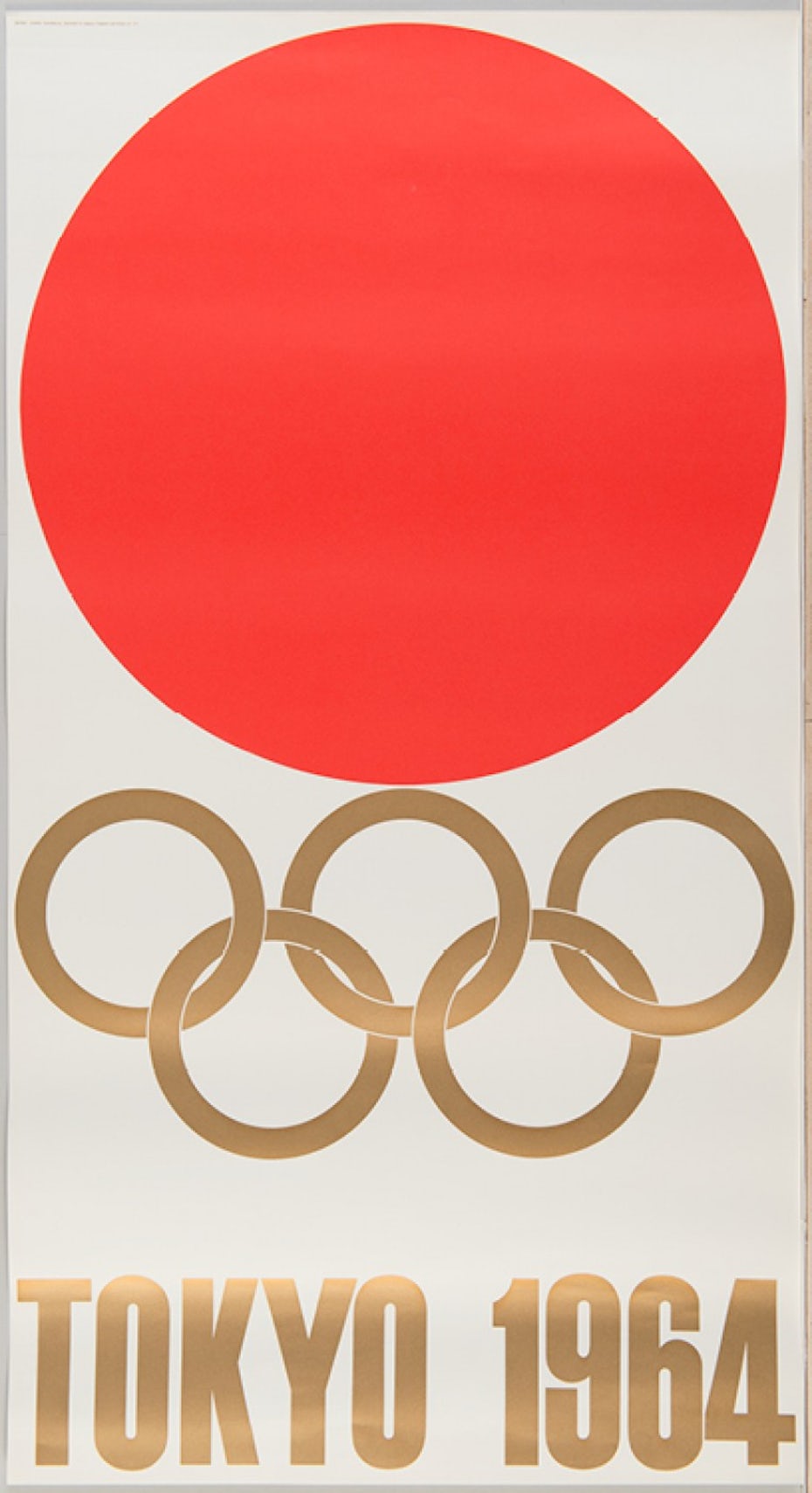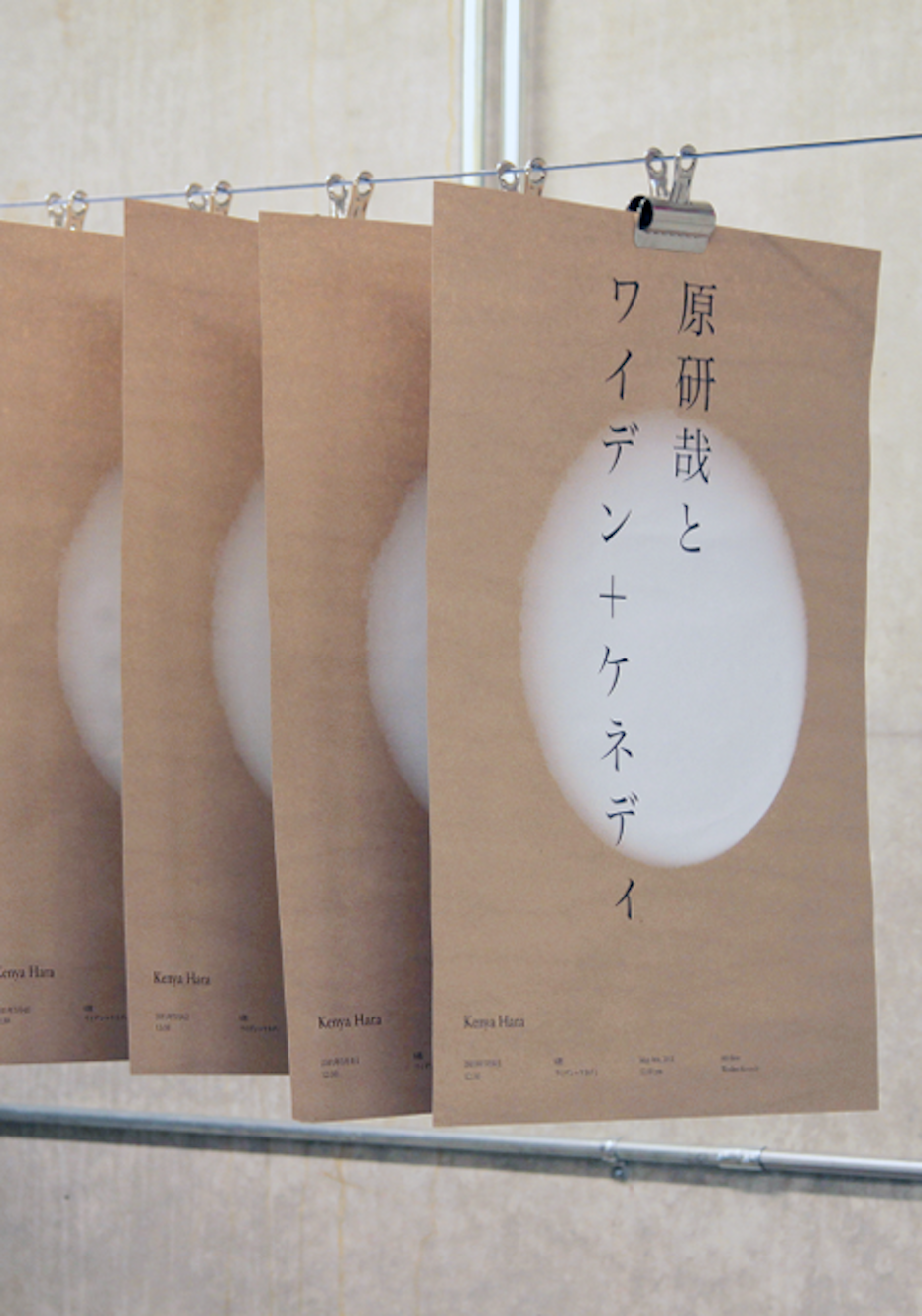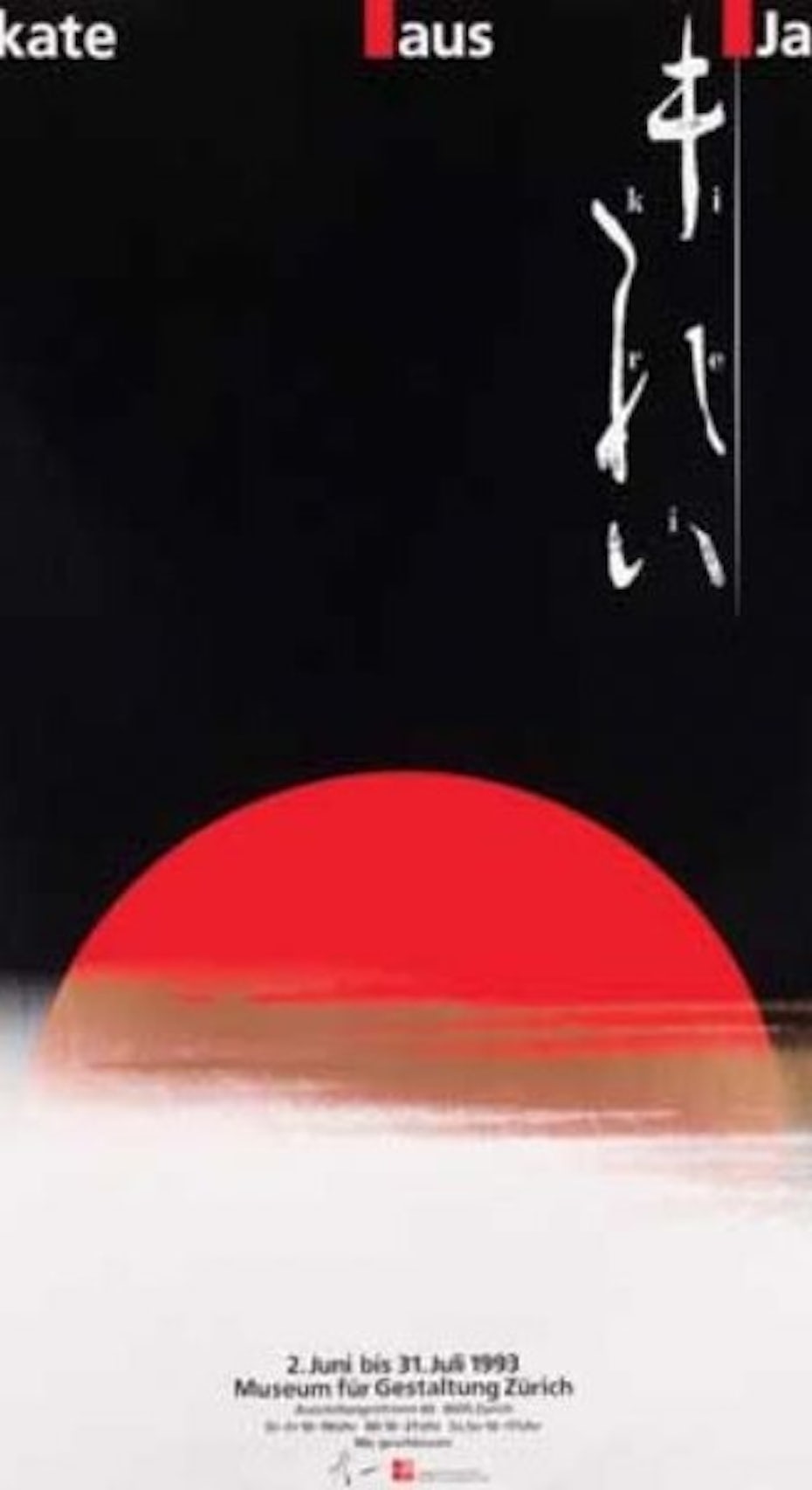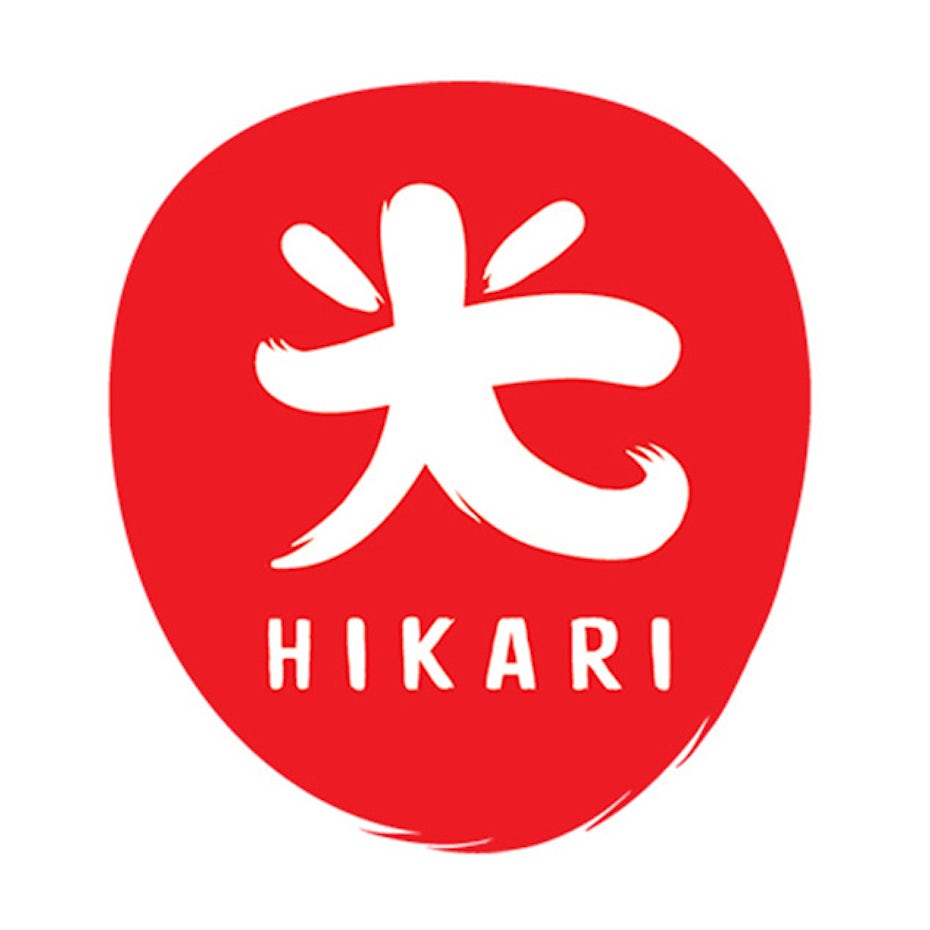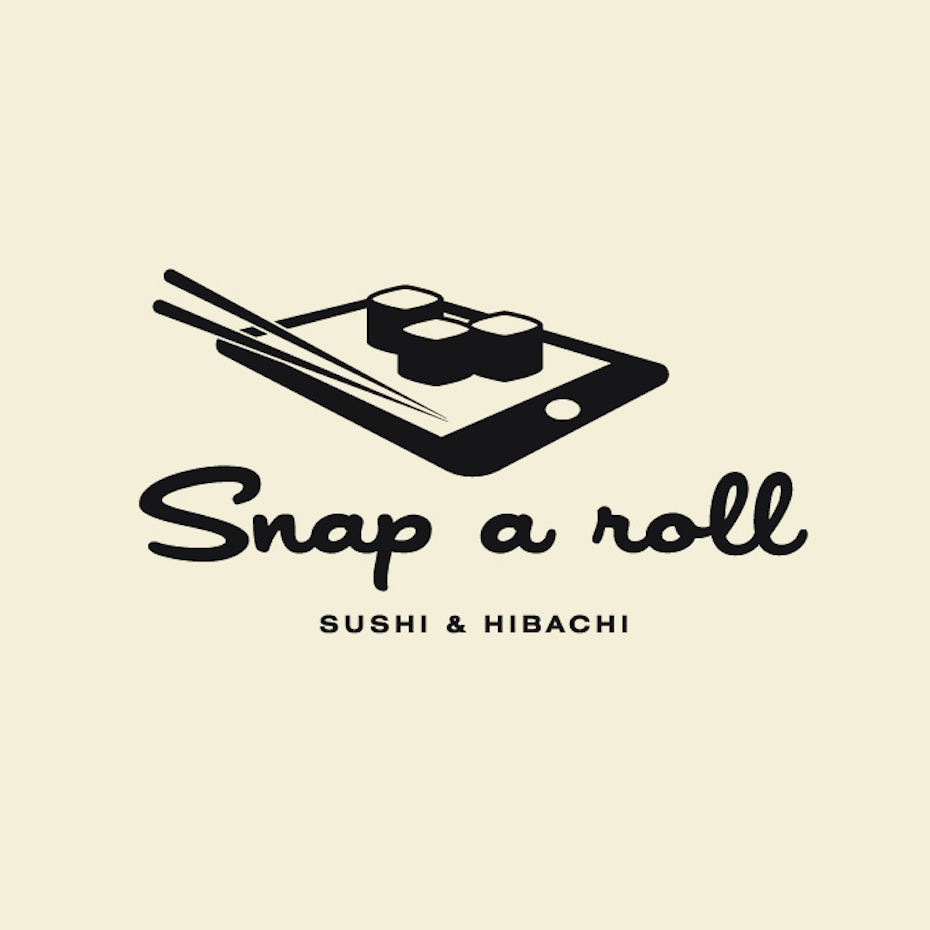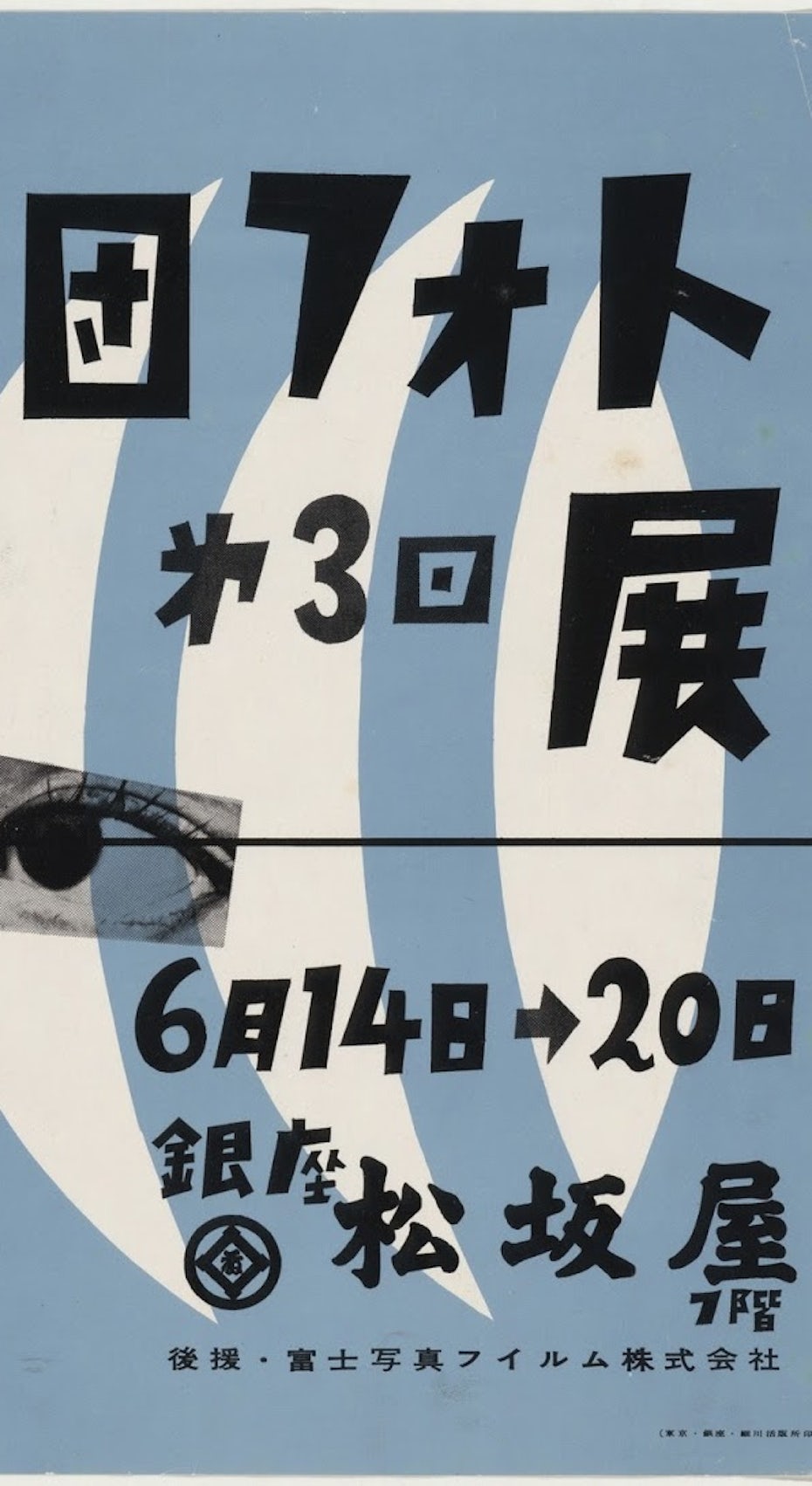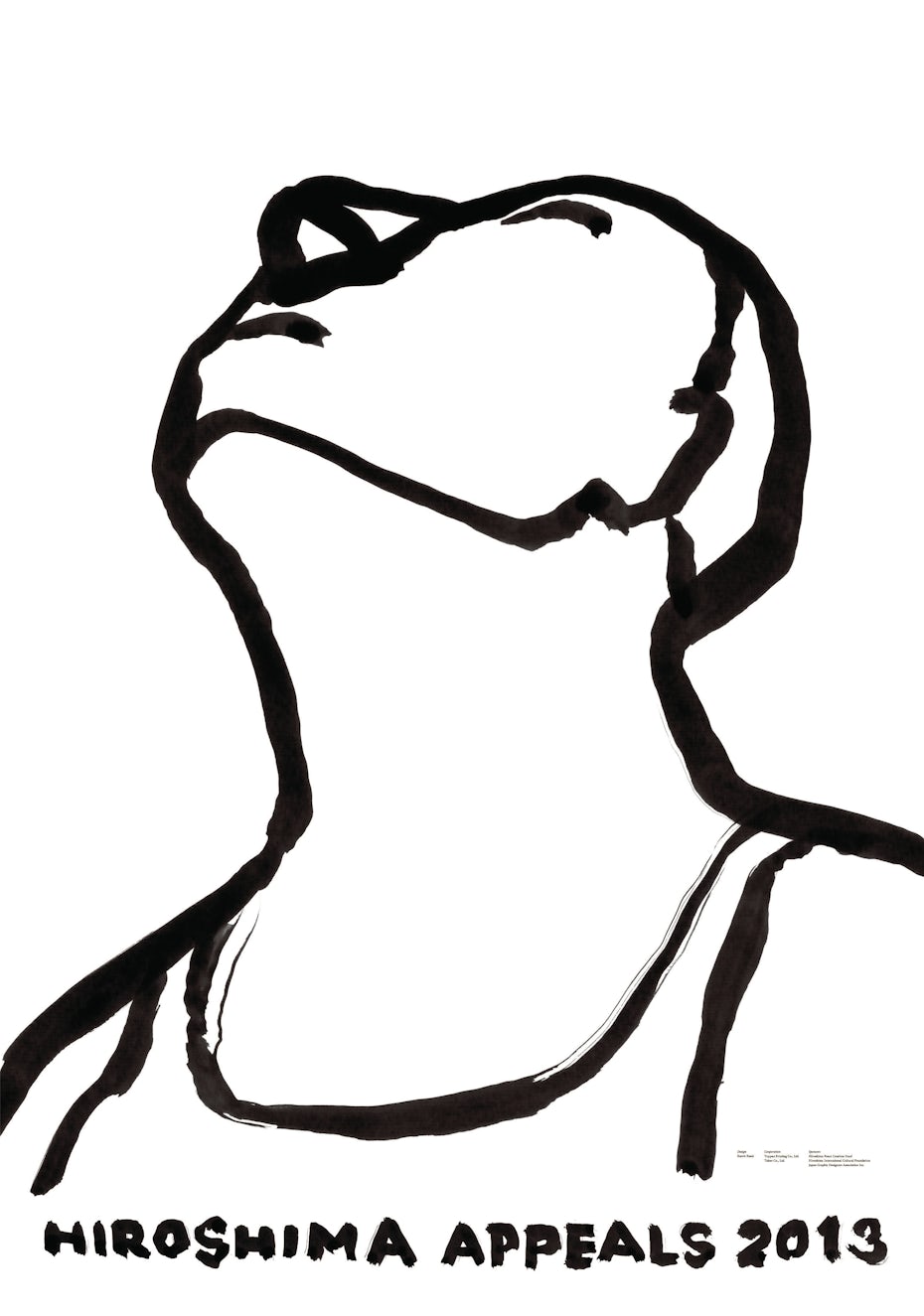
如何将日本元素融入到作品中去?
日本设计自豪地参考了数千年的日本传统艺术,同时也具有现代性和现代性。风格清晰有力的声音从简单的设计、几何图形和彩色斑点到响亮的吉祥物、可爱的图案和卡通。
从极简主义到流行,我们可以看到日本设计在整个西方及其他地区的影响力。
让我们一起来看看如何将日本设计灵感融入到自己的作品中!
日本设计简史
日本的设计总体上受到周围世界的严重影响。日本是一个拥有各种手工艺传统的国家。陶瓷,木版画,书法,折纸,歌舞伎剧场,以及最近的漫画和动漫都只是那里开发的一些艺术品。这些艺术形式影响了数百年的西方艺术和设计 - 例如,日本木刻版画影响了许多着名的西方艺术家,如古斯塔夫克里姆特和文森特梵高。
17世纪—19世纪
在江户时代(1603-1868),日本在经济和文化上蓬勃发展。设计和创意也蓬勃发展。日本广告商是他们销售产品和服务方式的先驱,创造了大规模的海报,印有排版的图形,以及日间相扑手和流行的歌舞伎剧场演员的明星插图。在Instagram出现之前,他们使用影响者营销已有数百年了!
浮世绘是日本木版画和绘画艺术的重要流派,也是在此期间发展起来的。它以女性美,歌舞伎,相扑选手,民间故事和风景等共同主题为特色。由于它很容易印刷,浮世绘变得分布广泛并迅速普及。
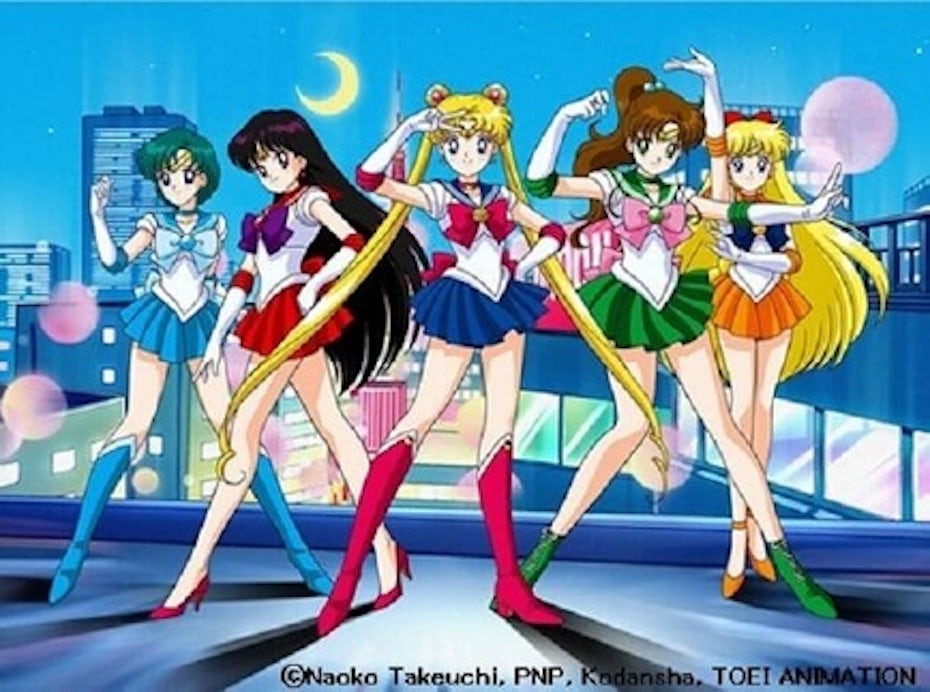
浮世绘后来演变成现代插图、漫画,动漫,甚至电子游戏。这些新风格具有更流行的审美和色彩,通过漫画,漫画小说和玩具对西方产生了巨大的影响。
19世纪后期
在明治时代(1868-1912),日本开放了与世界其他地区的边界,欢迎贸易文化和设计的交流。在西方艺术和设计的启发下,这导致未来50年日本设计的创造力爆炸式增长。
20世纪50年代到80年代
第二次世界大战后,日本经济大幅增长,最终成为世界第三大经济体。在战后年代的工业化和制造业的推动下,建构主义和包豪斯的风格激发了当今的设计,使用强烈的几何形状和日本象征。
20世纪90年代到21世纪
在90年代,日本设计以前所未有的方式爆炸。随着后现代主义和Photoshop和Illustrator等计算机软件的普及,人们可以获得一个全新的设计世界,日本人完全接受了它。
这一时期也让日本的设计更加关注社会责任。1991年至1992年,日本经济崩溃,国家进入了经济停滞时期,称为“失落的十年”,持续到2010年。
设计师试图通过摆脱过度行为并且带来平衡,从而在经济复苏期间积极影响人们工作。
今天,日本设计对全球变暖和污染等环境问题更加关注。由于人口众多且生活空间有限,设计师必须考虑人们如何消费他们的产品。因此,日本设计获得了相当自然的基调。
像Marie Kondo一样,摆脱任何不必要的东西。在传统的日本美学中,Wabi-Sabi是一个以接受禅宗和中国道教的不完美为中心的世界观。
基本上,它在不完美中找到快乐并摆脱所有不会激发快乐的东西。
Wabi-Sabi与现代主义有很多共同点,但它更直观,不对称,温暖,流畅。这种技术试图保持设计的本质而不会失去诗意。清洁,但不是无菌的,简单而聪明。
尝试将日本极简主义带入您的品牌,徽标,包装,网站等。
2.自然运动
许多最早的日本木版印刷块说明了自然以及世界如何不断变化和移动。这种连续感演变成现代漫画和明亮的包装。
3.自然
日本文化具有惊人(和令人生畏)的自然特征,如地震,火山和台风,对环境非常敏感。日本人民像其他人一样庆祝自然和季节。这种影响也带来了创意设计解决方案。
建筑设计借鉴了木材和石材等元素。在平面设计中,大自然进入包装材料,自然插图和泥土色调调色板。
4.几何
日本设计非常注重几何元素,因为形状具有更深刻的文化含义。
正方形和矩形代表自然界中不常见的人造形式,通常用于制作和服,漆盒,箱子,屏风和一些陶瓷的轮廓。曲线和圆弧代表直觉和灵感。
5.排版
日语排版比西方字母复杂得多,书法在日本设计中起着巨大的作用 - 绘画字母本身就是一种艺术形式。
现代日语由三种基本文字组成:汉字(汉字表意符号)和平假名和片假名(语音符号)。因此,日语的字体数量有限,而且为任何设计项目定制排版是很常见的。
6.象征意义
日本的民间传说,所有的东西都有自己的精神 - 甚至是像石头或盒子一样无生命的东西。这就是为什么在产品中添加面孔和类似人的品质如此常见的原因。你会看到这广泛用于广告,海报,包装和品牌。
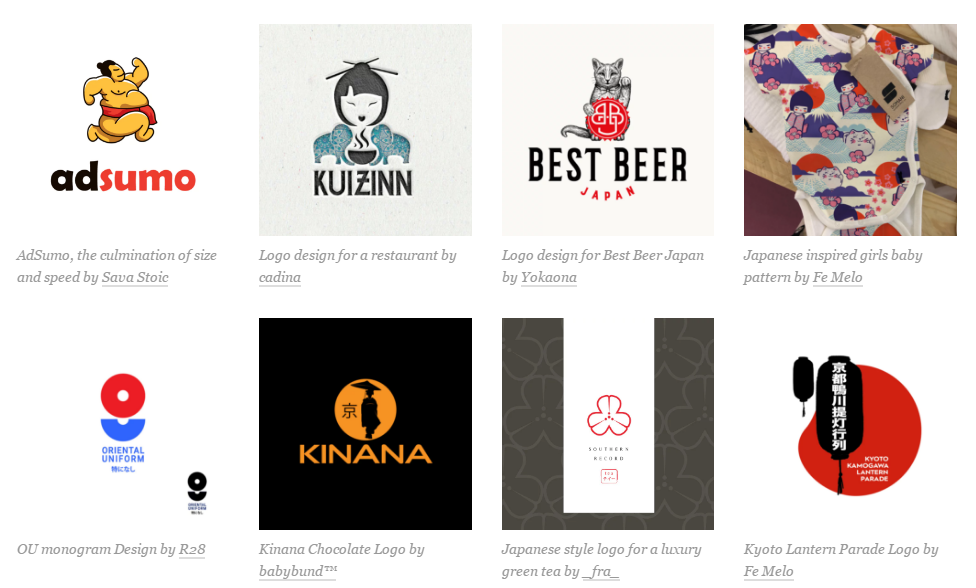
传统融入了日本设计,如果你看到很多富士山,旭日,幸运猫或相扑选手的照片,不要感到惊讶。符号的运用也有许多,云意味着优雅和高地位,山脉代表着不动,水象征着力量和韧性。
7.日本插画
漫画是日本漫画或图画小说。与美国漫画相比,日本漫画更具视觉效果,文字更少。漫画也有广泛的流派,吸引更大的人口。
动漫是一部日本漫画(通常以漫画为基础,但不是常规)以其独特的图形特征而闻名,如巨大的眼睛,“洋娃娃”的面孔和可爱的角色。动漫是一个广泛的术语,适用于所有年龄段的更广泛的流派。
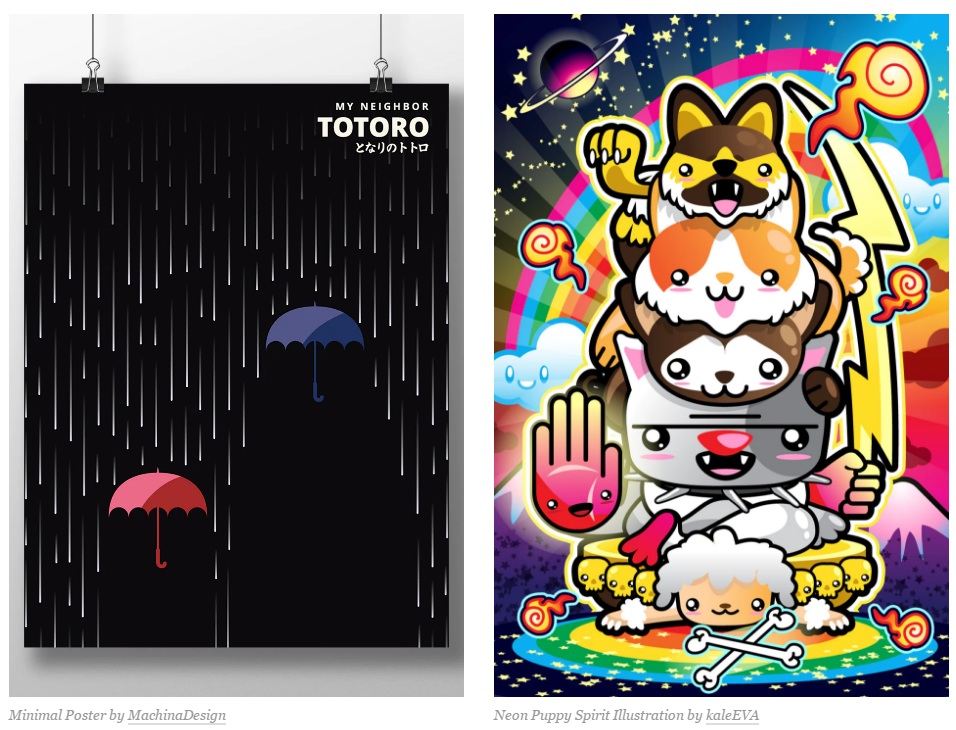
8.图案
从shiburi艺术到木刻版画,日本设计中充满了几何和花卉图案。
Hanakotoba是对花的研究以及每朵花的精神意义。根据日本的传统,粉红色象征着愈合,红色象征着爱,白色象征着美德。
9.食物
从拉面到寿司等,日本料理在全世界都很受欢迎。设计和美食甚至融合了怀石料理或日式料理,使用当地时令食材来庆祝季节。
将日本设计融入到自己的作品中去!!!
日本设计有无数不同的风格和视觉技术,并不可能将它们全部命名。它们每个都有一些非常流畅和自然的东西,这意味着规则总是可以变化的,这就是日本艺术今天继续影响设计的原因。尝试混合和匹配样式,就会发现真正独特的东西!